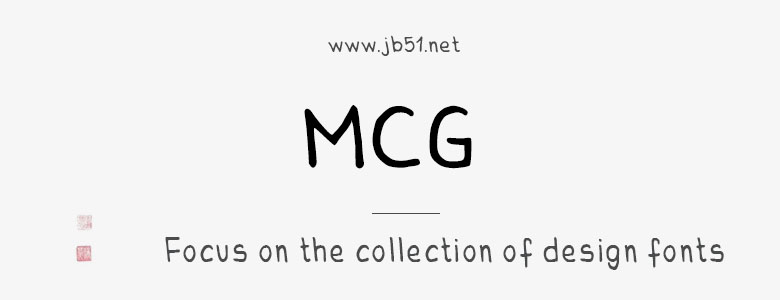
MCG英文手寫(xiě)字體,字體筆觸適中,字形端正,具有很好的視覺(jué)感,適合應(yīng)用于藝術(shù)設(shè)計(jì)、平面宣傳設(shè)計(jì)、網(wǎng)頁(yè)設(shè)計(jì),書(shū)法字帖等領(lǐng)域。有需要的朋友快來(lái)本站下載使用吧。